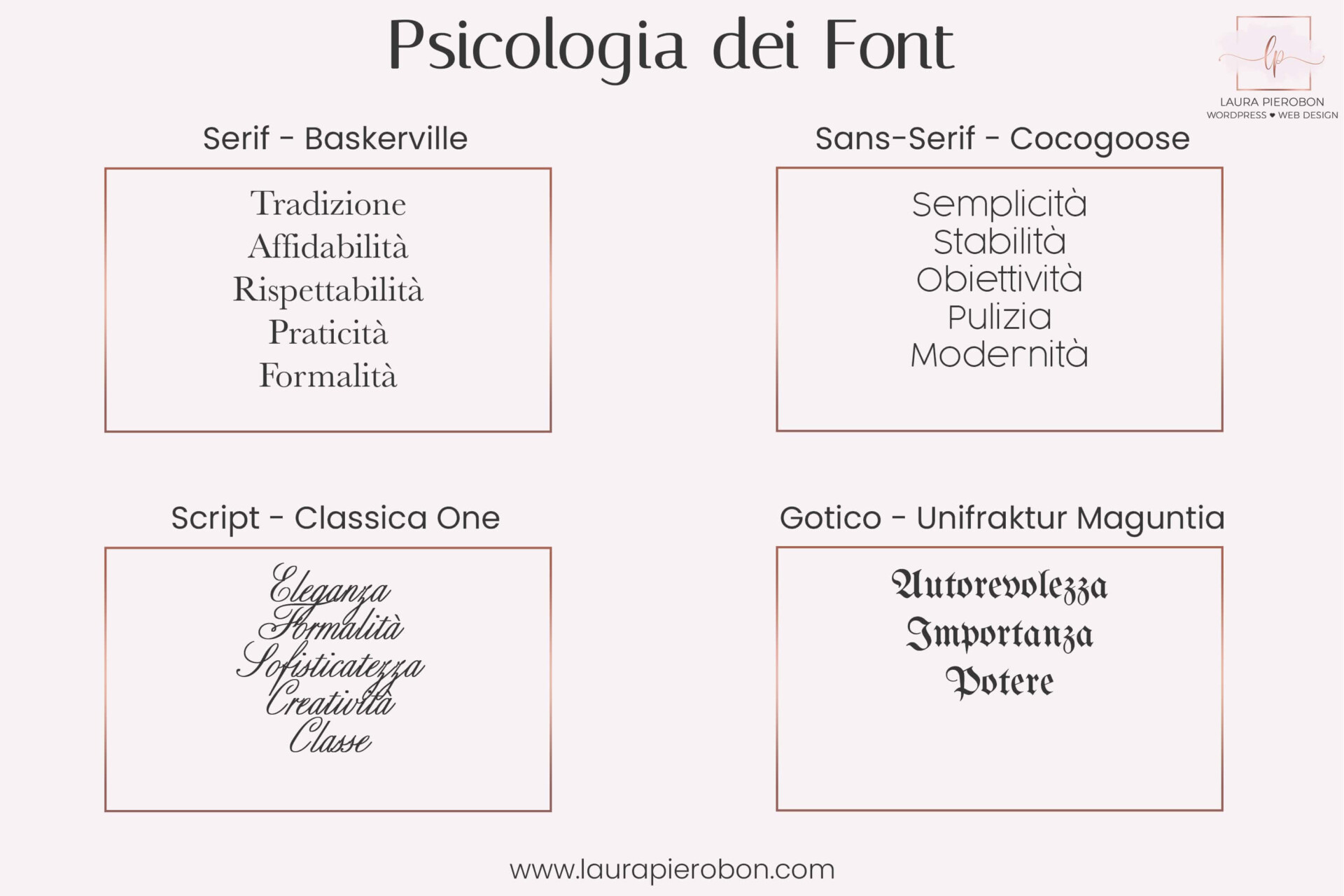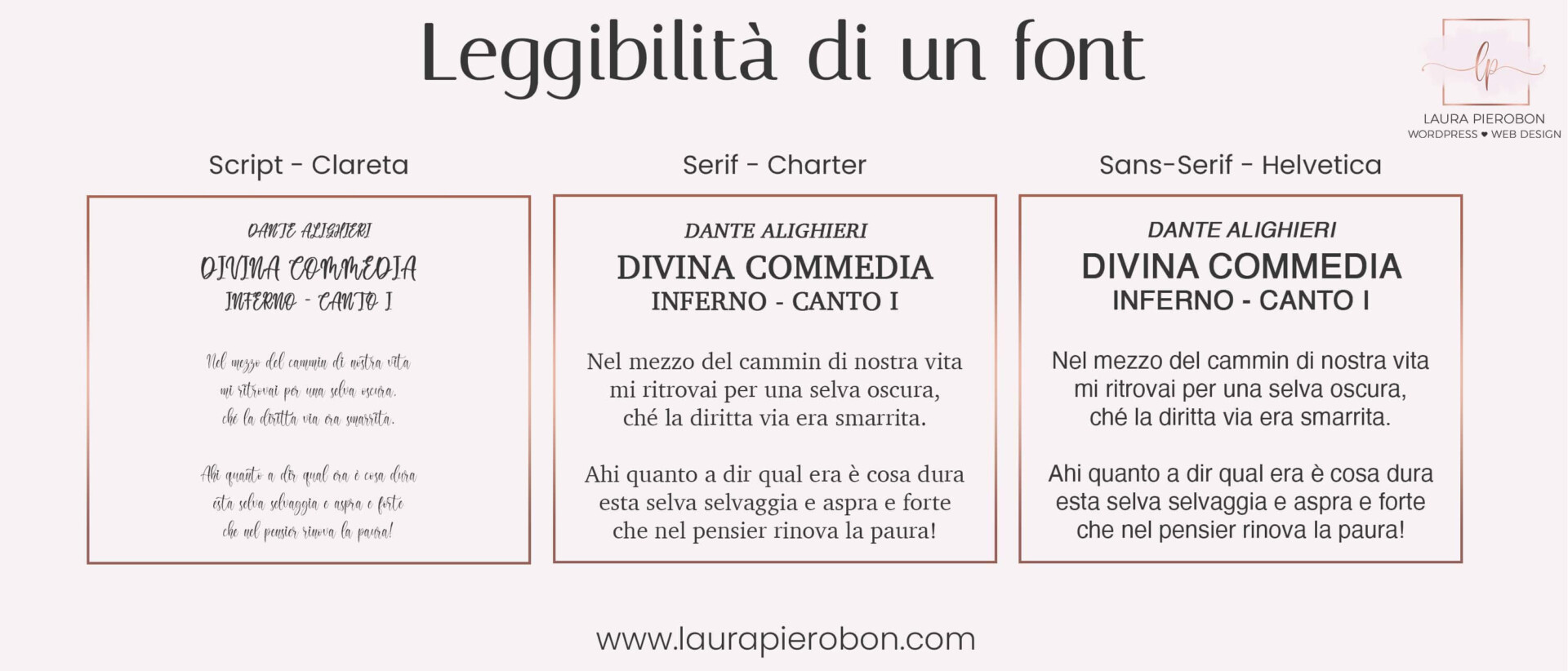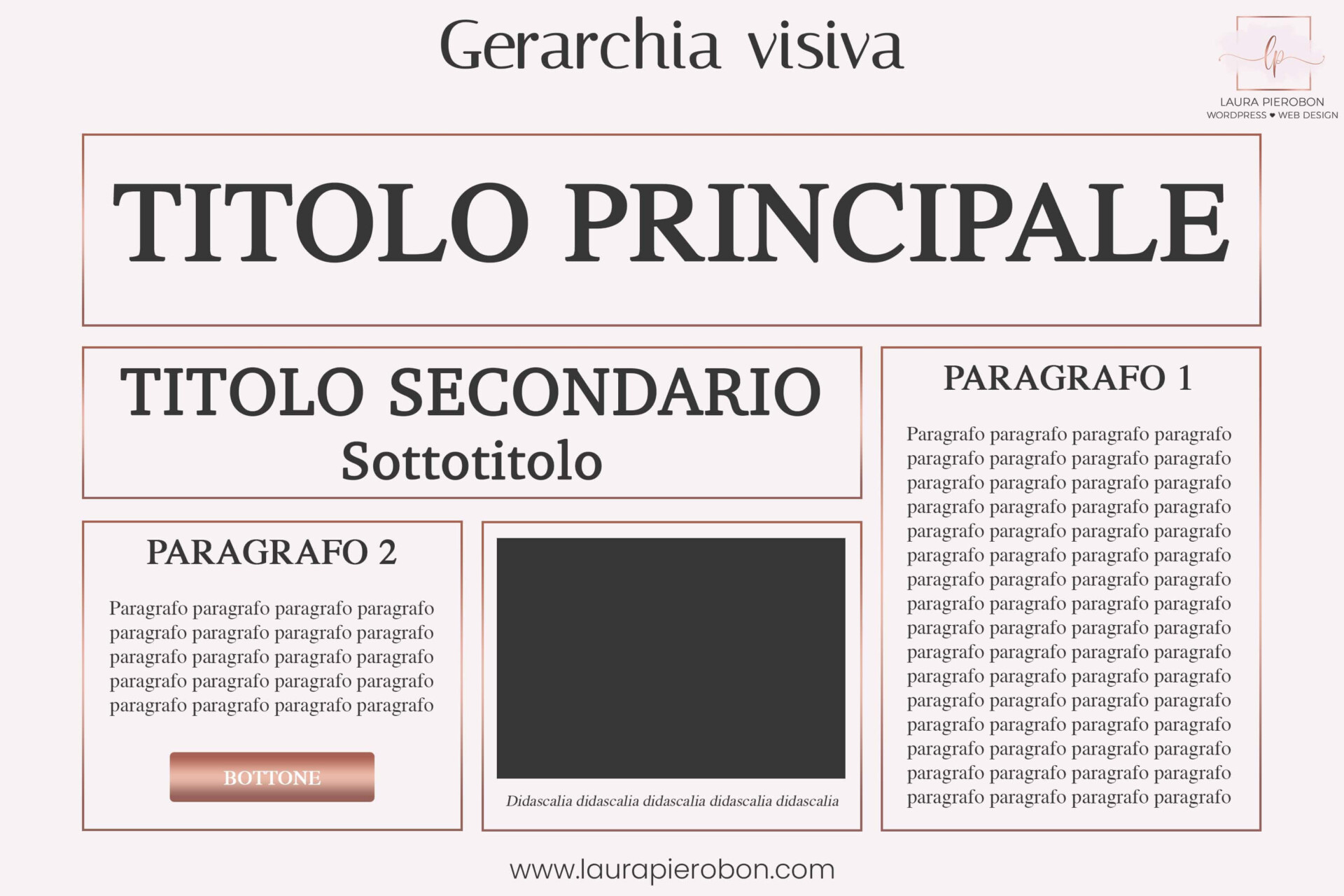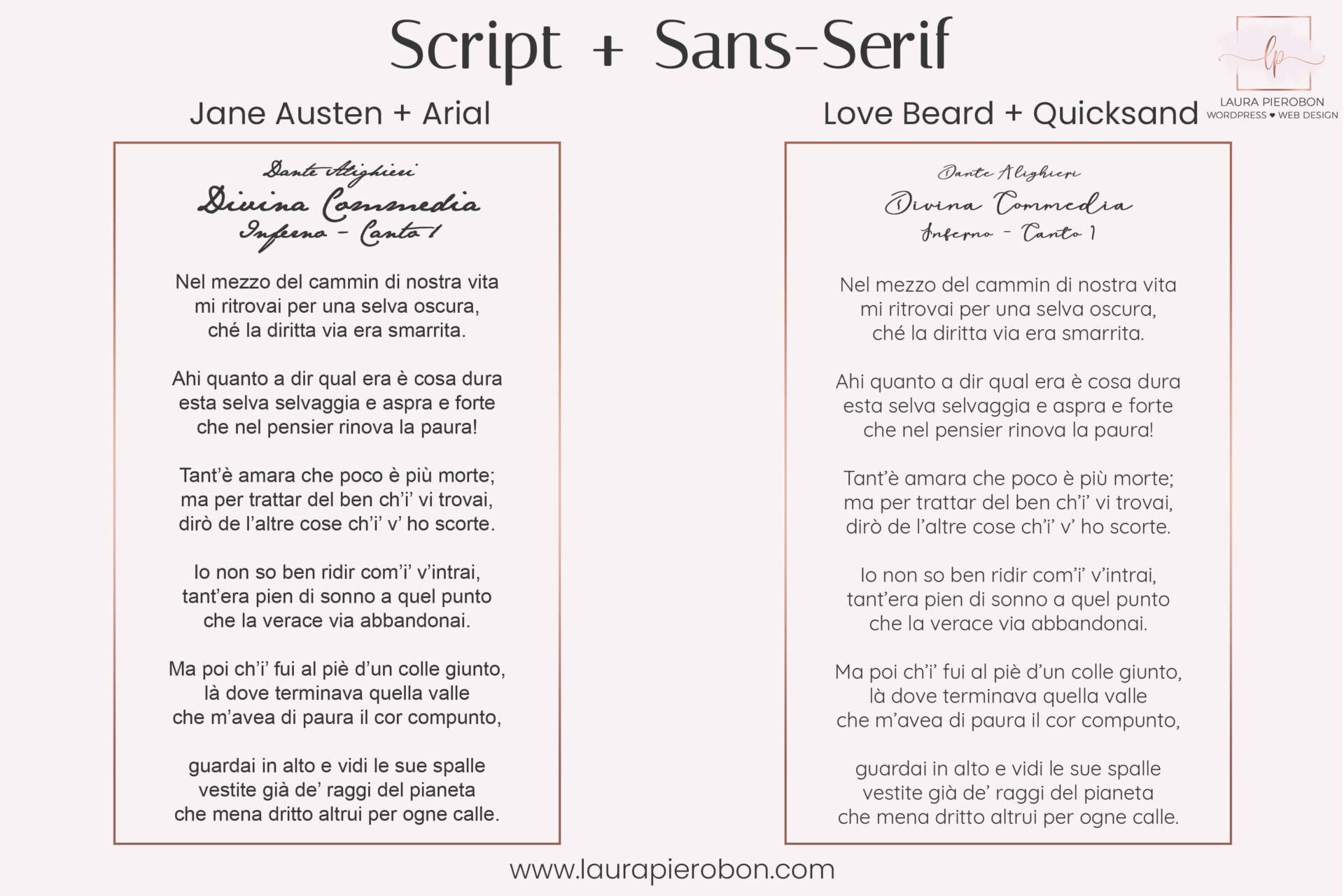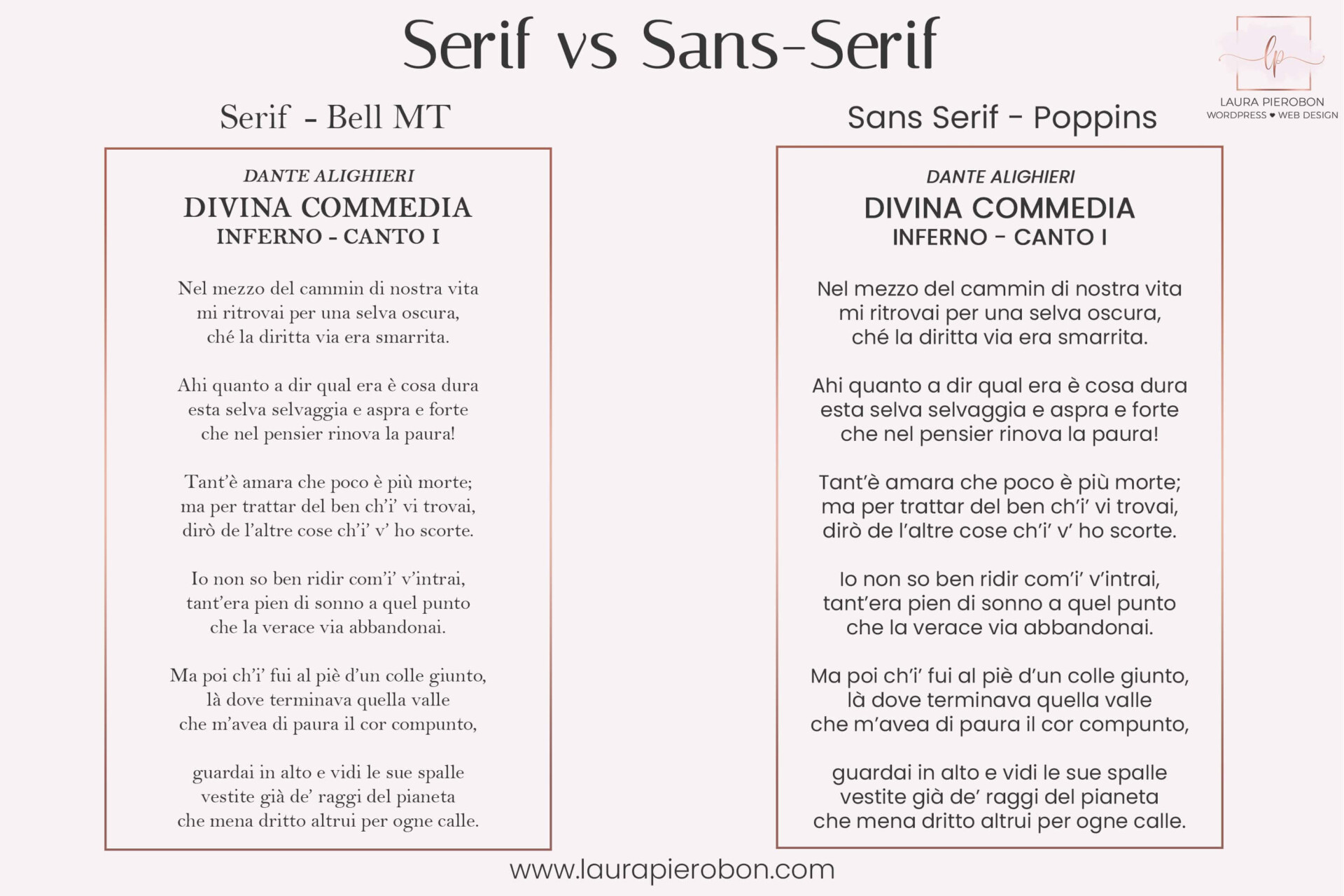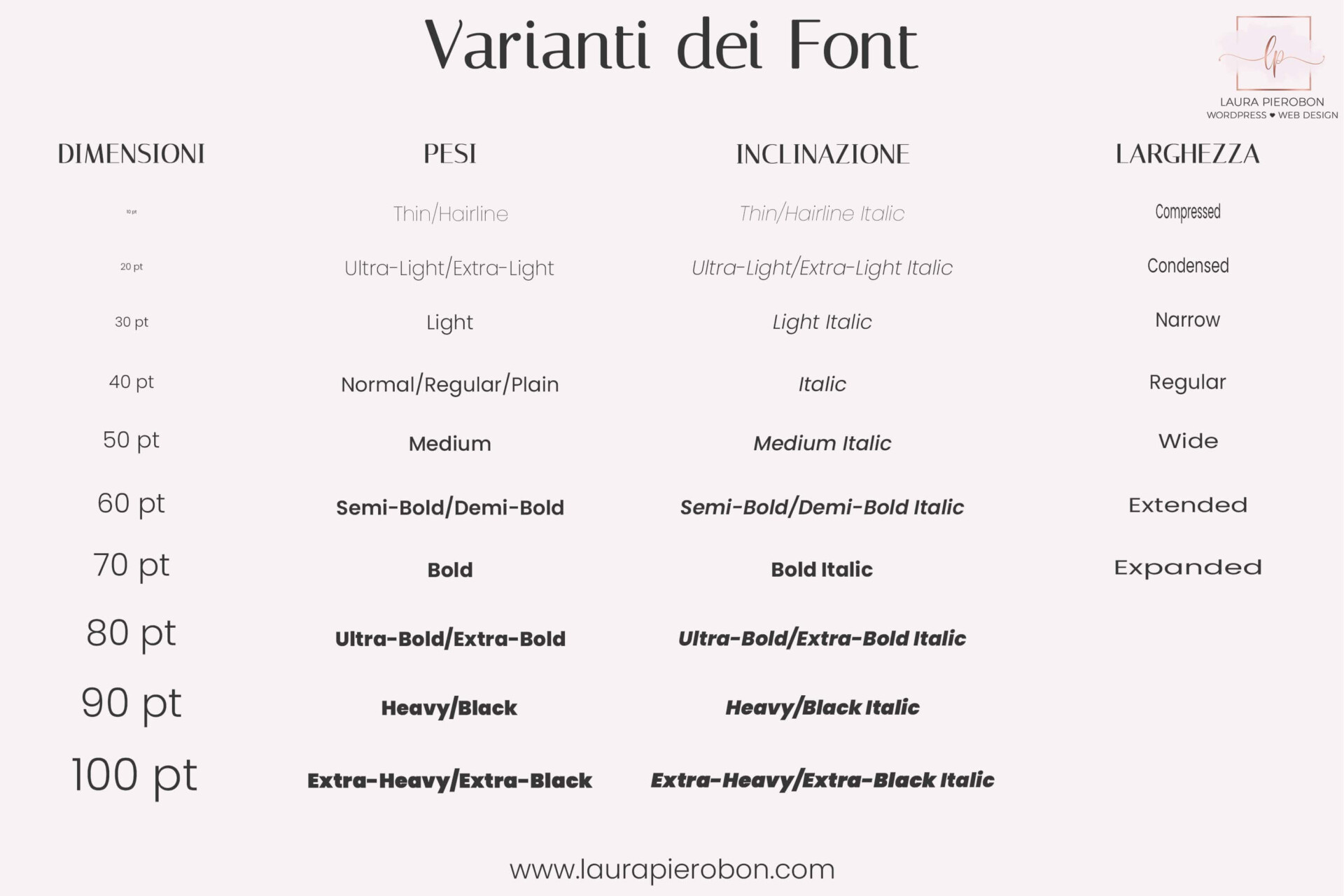
Quando inizi a lavorare sulla tua identità visiva – che sia per il sito web, il logo o i contenuti social – ci sono due elementi che fanno subito la differenza: i colori e i font, che insieme rendono il tuo brand riconoscibile, coerente e credibile.
In questo articolo, invece, ci concentriamo sui font. Non solo su “quali sono belli”, ma su come sceglierli e abbinarli in modo consapevole, così che parlino davvero di te e del tuo progetto.
Cos’è un font (e perché spesso si fa confusione)
Nel linguaggio comune usiamo la parola font per indicare tutto, ma in realtà esistono alcune distinzioni importanti.
- Carattere: una singola lettera, numero o simbolo (A, 1, !).
- Glifo: la rappresentazione grafica di un carattere (A, a, À, æ…).
- Carattere tipografico (Typeface): l’insieme coerente di tutti i caratteri con lo stesso stile grafico (es. Poppins, Italiana).
- Font: il file digitale che contiene una o più varianti di un carattere tipografico (peso, stile, larghezza).
Capire questa differenza ti aiuta a fare scelte più consapevoli quando lavori sul tuo sito o sulla tua immagine coordinata.
Tipologie di font: le grandi famiglie
Per orientarsi tra i tantissimi font esistenti, si usano alcune categorie principali.
Serif
Sono i font “con grazie”. Trasmettono tradizione, affidabilità, eleganza.
Sono spesso usati nella stampa e nei brand più classici o istituzionali.
Sans-serif
Sono i font “senza grazie”. Puliti, moderni, molto leggibili sul web.
Ideali per siti, testi lunghi e brand contemporanei.
Script / Calligrafici
Imitano la scrittura a mano. Eleganti e creativi, ma da usare con moderazione, soprattutto nei testi lunghi.
Decorativi
Font particolari, espressivi, pensati più per titoli o dettagli che per il corpo del testo.
La psicologia dei font: cosa comunicano davvero
Proprio come i colori, anche i font trasmettono emozioni.
- I serif parlano di autorevolezza e solidità
- I sans-serif comunicano semplicità e chiarezza
- Gli script evocano creatività, femminilità, raffinatezza
- I decorativi attirano l’attenzione, ma vanno dosati con cura
La scelta del font deve essere coerente non solo con il tuo gusto personale, ma con il messaggio che vuoi trasmettere e con il pubblico a cui ti rivolgi.
Come scegliere i font giusti per il tuo progetto
1. Parti dalla leggibilità
Un font può essere bellissimo, ma se non si legge… non funziona.
Per testi lunghi (articoli, pagine del sito) privilegia font semplici e ben leggibili.
2. Considera il contesto
Un font può funzionare su una copertina Instagram ma non su un sito web.
Chiediti sempre: dove verrà usato?
3. Pensa al tuo brand, non alle mode
Le tendenze passano, l’identità resta. Scegli font che possano accompagnarti nel tempo.
Come abbinare i font (senza creare confusione)
Stabilisci una gerarchia visiva
Titoli, sottotitoli, testo, pulsanti: ogni elemento ha un ruolo diverso.
I font servono anche a guidare l’occhio.
Usa pochi font
Due font sono spesso più che sufficienti. Tre solo se sai bene cosa stai facendo.
Strumenti utili per trovare combinazioni che funzionano
Se vuoi fare qualche prova pratica, questi strumenti sono ottimi alleati:
- Google Fonts – libreria gratuita vastissima
- Fontjoy – combinazioni automatiche
- Fontpair – abbinamenti già testati
- Canva Font combinations – semplice e intuitivo
⭐ Cosa ti porti a casa con questo articolo
- font, typeface e glifi non sono la stessa cosa, e conoscerne la differenza aiuta a usare la tipografia con maggiore consapevolezza
- le diverse famiglie di font comunicano sensazioni diverse e influenzano la percezione del brand
- la scelta di un font non è solo estetica, ma dipende da leggibilità, contesto e obiettivi comunicativi
- abbinare i font in modo efficace richiede equilibrio, gerarchia e contrasto, non accumulo